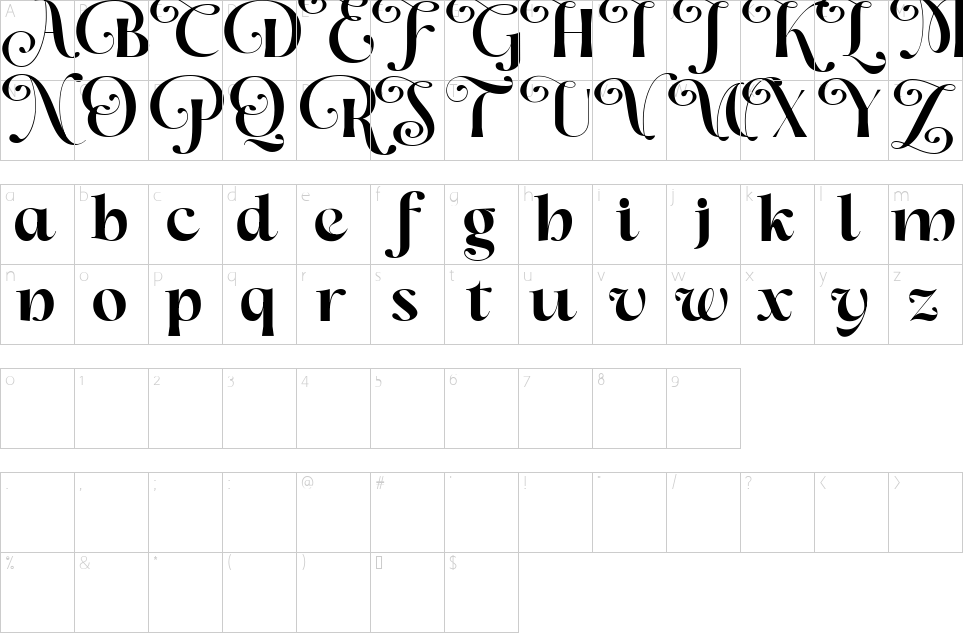
A Dh Milate é uma fonte moderna e elegante disponível para download tanto no Windows quanto no Mac. Desenvolvida pelo estúdio Dharmas Studio, a fonte ganhou grande popularidade, sendo baixada 836 vezes desde sua disponibilização. Seu estilo fluido e arredondado combina perfeitamente com textos em blogs de design gráfico ou sites pessoais que buscam um equilíbrio entre funcionalidade e simplicidade. A Dh Milate é uma opção ótima para aqueles procurando por uma fonte moderna, versátil e fácil de ler, sem precisar desembolsar nenhum valor adicional. Além disso, a estética da fonte permite que você personalize a aparência de seus documentos, seja em postagens no blog, relatórios ou até mesmo em designs gráficos profissionais. Seja designer de web, blogger ou profissional do design gráfico, a Dh Milate é uma opção perfeita para sua necessidade.